타이포그래피 기초를 처음부터 제대로 배우는 방법
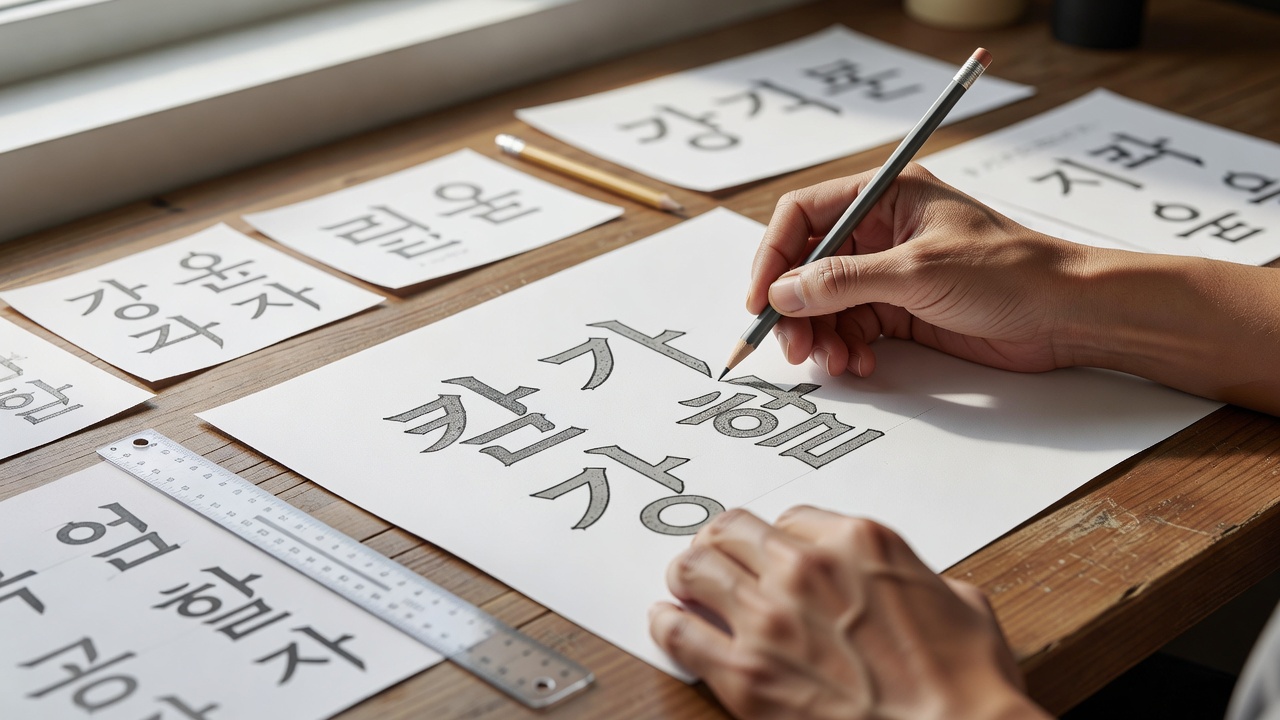
타이포그래피 기초는 글자 모양, 간격, 계층 구조를 이해하는 것부터 시작합니다. 이 세 가지 요소를 먼저 파악하면 어떤 서체를 선택하든 일관된 가독성과 시각적 질서를 만들 수 있습니다. 2026년 현재에도 초보자가 가장 많이 놓치는 부분이 바로 이 기본 개념의 순서입니다.
타이포그래피 기초가 중요한 이유
타이포그래피는 단순히 글자를 예쁘게 배치하는 작업이 아닙니다. 독자가 내용을 얼마나 빠르고 정확하게 이해하는지를 결정하는 시각적 언어입니다. 기초를 제대로 다지지 않으면 이후에 고급 기법을 배워도 전체적인 균형이 무너지기 쉽습니다.
2026년 현재 디자인 교육 현장에서도 타이포그래피 기초를 건너뛰고 바로 실무 툴을 다루는 경우가 많습니다. 그러나 실제 결과물의 완성도는 기초 이해도에 따라 크게 갈립니다. 따라서 학습 순서를 명확히 정하는 것이 중요합니다.
글자 모양의 기본 요소
글자 모양은 스트로크, 획의 두께, 종횡비, 세리프 유무 등으로 구성됩니다. 각 요소가 어떻게 조합되는지를 관찰하는 훈련이 필요합니다. 특히 한글은 자음과 모음이 결합하는 구조 때문에 로마자보다 형태 분석이 더 복잡합니다.
초보자는 먼저 같은 계열의 서체 여러 개를 비교하며 차이를 찾아보는 연습을 추천합니다. 이 과정에서 ‘두께 대비’, ‘오픈 카운터’, ‘터미널 모양’ 같은 용어를 자연스럽게 익힐 수 있습니다.
자간·행간·단락 간격 다루기
| 요소 | 기본 기준 | 조정 목적 | 주의점 |
|---|---|---|---|
| 자간 | 0~+50 | 가독성 확보 | 과도한 마이너스는 글자 붙음 현상 유발 |
| 행간 | 140–180% | 줄 간 분리감 | 본문은 150% 내외가 가장 안정적 |
| 단락 간격 | 1행–1.5행 | 문단 구분 | 제목과 본문 사이에는 더 넓게 |
간격은 글자 모양만큼이나 전체 인상을 좌우합니다. 특히 모바일 환경에서는 행간을 조금 더 넓게 잡는 것이 현재 추세입니다.
계층 구조로 정보 전달하기
타이포그래피에서 계층 구조는 크기, 굵기, 색상, 위치를 통해 정보를 우선순위화하는 작업입니다. 제목, 부제, 본문, 캡션 각각에 명확한 역할을 부여해야 합니다.
H1은 가장 강한 존재감을, 본문은 중립적인 가독성을, 캡션은 보조 정보로 작게 처리하는 것이 일반적입니다. 이 규칙을 지키지 않으면 독자는 어디를 먼저 읽어야 할지 혼란스러워합니다.
한글 타이포그래피에서 주의할 점
한글은 자음과 모음의 결합 방식 때문에 같은 서체라도 조합에 따라 밀도가 달라집니다. 특히 ‘ㅏ, ㅓ, ㅗ, ㅜ’ 같은 모음이 들어간 글자는 주변 여백이 부족해 보일 수 있습니다.
따라서 한글 전용 서체를 선택할 때는 실제 문장을 입력해 테스트하는 과정이 필수입니다. 로마자 기준으로만 평가하면 한글 문서에서 균형이 깨지기 쉽습니다.
실전에서 자주 하는 실수와 해결
많은 초보자가 서체를 너무 많이 섞어 사용하는 실수를 합니다. 2026년 현재에도 2–3개 이상의 서체를 동시에 쓰는 경우가 흔한데, 이는 오히려 산만한 인상을 줍니다.
또 다른 흔한 실수는 행간을 너무 좁게 설정하는 것입니다. 특히 긴 문장을 다룰 때는 150% 이상의 행간을 확보해야 피로도가 줄어듭니다.
학습에 도움이 되는 도구와 리소스
- Figma: 실시간으로 간격과 계층을 확인하며 작업 가능
- Glyphs Mini: 한글 서체 구조를 분석하는 데 유용
- Google Fonts + 한국어 필터: 무료로 한글 지원 서체를 테스트할 수 있음
이 외에도 실제 인쇄물을 스캔해 분석하거나, 기존 디자인 사례를 역으로 분해해보는 방법도 효과적입니다.
타이포그래피 기초를 배우는 데 얼마나 걸리나요?
개인차가 있지만, 매일 1시간씩 집중해서 3–4개월 정도면 기본적인 판단력을 갖출 수 있습니다. 중요한 것은 양보다 꾸준한 관찰과 비교 연습입니다.
한글과 영문을 동시에 사용할 때 어떤 서체를 골라야 하나요?
가능하면 같은 디자이너가 만든 패밀리 서체를 사용하는 것이 가장 안전합니다. 그렇지 않다면 중성적인 산세리프 계열에서 두 서체의 두께와 비율을 맞추는 작업이 필요합니다.
행간은 정확히 몇 퍼센트가 정답인가요?
본문 기준으로 150–160%가 가장 무난합니다. 다만 제목이나 짧은 문장에서는 130% 이하로 낮춰도 괜찮습니다.
무료 서체만으로도 충분히 좋은 결과물을 만들 수 있나요?
네, 가능합니다. 다만 무료 서체는 완성도가 들쭉날쭉하기 때문에 실제 사용 전에 여러 문장에서 테스트해보는 과정이 필수입니다.
타이포그래피를 배우기 전에 먼저 알아야 할 것이 있나요?
기본적인 디자인 원리, 특히 대비와 여백 개념을 미리 이해하고 있으면 훨씬 수월합니다. 색상 이론은 나중에 보완해도 됩니다.
타이포그래피 기초는 한 번 제대로 다져두면 이후 모든 디자인 작업의 기반이 됩니다. 지금부터라도 글자 모양, 간격, 계층 구조를 순서대로 관찰하는 습관을 들여보세요. 실제 프로젝트에 적용하며 궁금한 점이 생기면 언제든 문의해 주시기 바랍니다.